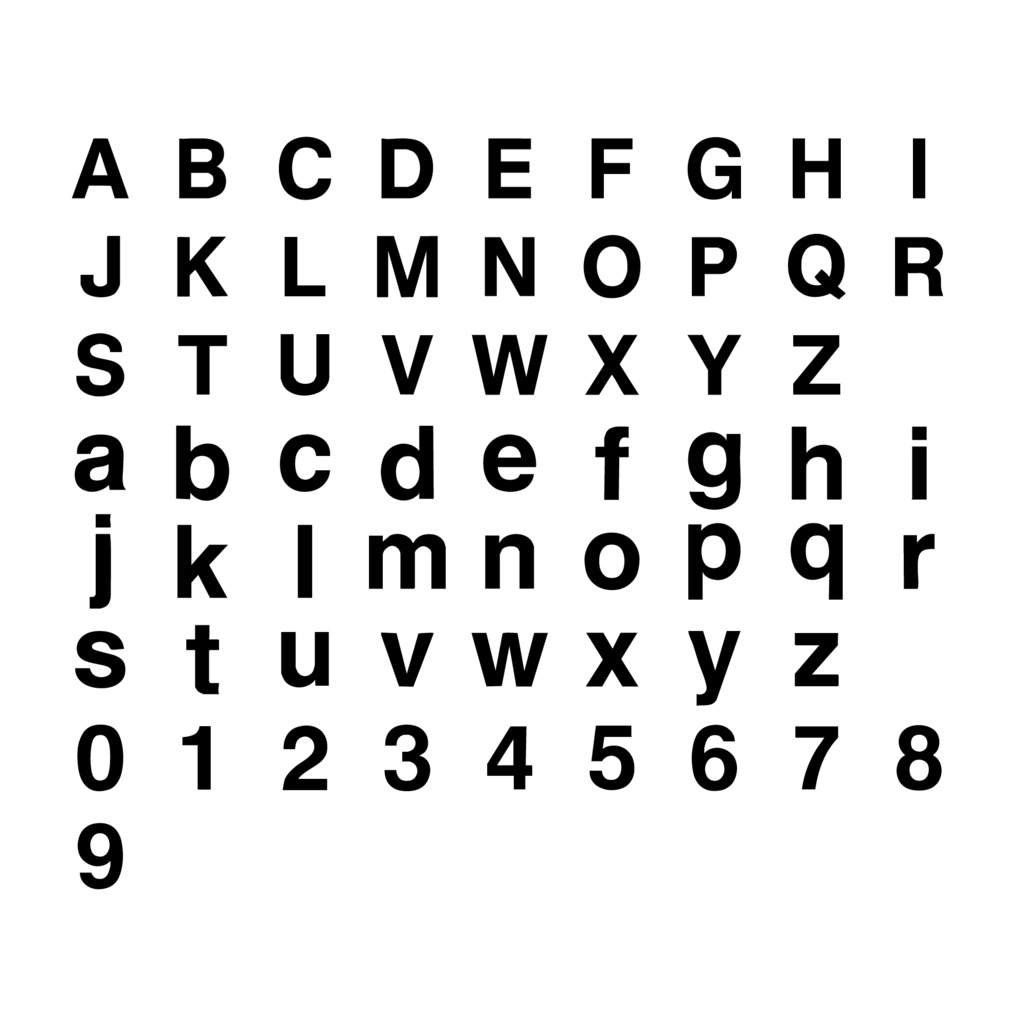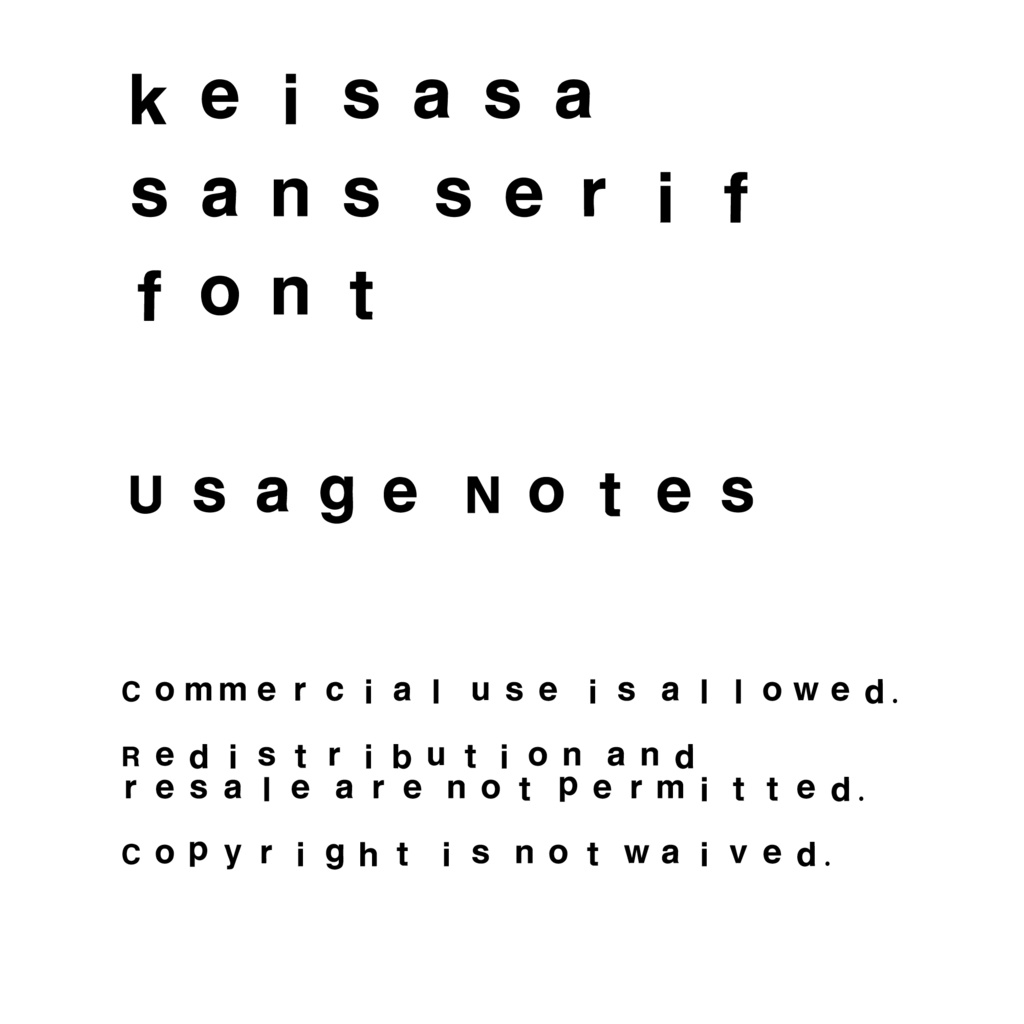
【商用可】keisasa_sans_serif_font︱ モダン系サンセリフフォント
keisasa sans serif font は、シンプルかつ視認性の高いサンセリフ書体です。 無駄のない直線と安定感のある形状は、あらゆるデザインに自然に馴染みます。 ロゴ、ポスター、見出し、パッケージデザイン、Webデザインなど、幅広い用途でご利用いただけます。 商用利用可 再配布・再販売不可 著作権は放棄しておりません keisasa sans serif font is a clean and highly legible sans serif typeface. With its minimalist lines and balanced shapes, it blends seamlessly into any design. Perfect for logos, posters, headlines, packaging, and web design. Commercial use allowed Redistribution and resale prohibited Copyright not waived